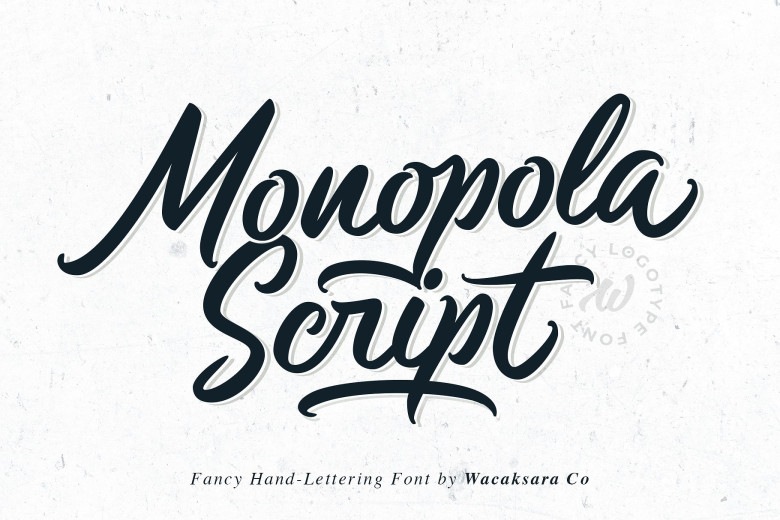
КАКИЕ БЫВАЮТ ШРИФТЫ
Если вы учились на графиков, скорее всего, вы помните основы. Если нет — я рада с вами ими поделиться! Важно отметить, что «в настоящее время общепринятая классификация шрифтов отсутствует, любая схема отражает личное мнение ее составителей». (Компания «Паратайп», paratype.ru). Поэтому нижепривёдённая классификация — это не подробная профессиональная классификация, а скорее шпаргалка для тех, кому надо вспомнить или просто полезно иметь под рукой небольшую справку.
Итак, какие бывают
шрифты? Одна из возможных классификаций разделяет шрифты по стилистическому
признаку на 4 группы: антиквы, гротески, декоративные и акцидентные, а также
рукописные и каллиграфические шрифты.
1) Антиквенные шрифты
Антиквенные шрифты (или антиквы) — это шрифты с засечками. Они могут быть контрастными или одноширинными, прямыми или курсивными, с исторической формой знака или современной. Главный отличительный элемент — засечка — может быть брусковой, треугольной, тонкой, толстой, скруглённой, острой, в общем, практически любой. Засечка всегда зависит от исторического контекста или от фантазии автора современного шрифта. Более подробно о группе антикв и их истории можно почитать в статье на Википедии (ссылка: https://ru.wikipedia.org/wiki/%C0%ED%F2%E8%EA%E2%E0). В рамках прикладной классификации («шпаргалки») можно не обращаться к истории, но для более глубокого изучения шрифтов я рекомендую ознакомиться с антиквами более подробно.
2) Гротески
Гротески, или как их
ещё называют, рубленые шрифты, это собственно шрифты без засечек.
Вначале их
использовали исключительно для акциденции, но в XX веке стали использоваться
для набора больших масс текста. Характеризуются, как правило, малой
контрастностью или полным отсутствием визуального контраста между основными и
соединительными штрихами. Иногда
к гротескам относят также так называемую ленточную антикву — умеренно контрастный
шрифт без засечек, конструкция которого повторяет один из видов антиквы. Сейчас гротески повсеместно используются в дизайне: сайтов, интерфейсов, рекламе, в журналах и т.д.
3) Декоративные и акцидентные шрифты
К этой группе относятся шрифты специально
предназначенные для акцидентного набора (то есть для выделения, например,
заголовков или важных элементов), использующиеся в декоративных целях, или
имитирующие определенный исторический стиль (например, модерн и т.д.). Форма
знака может быть изменена в целях создания определённого настроения.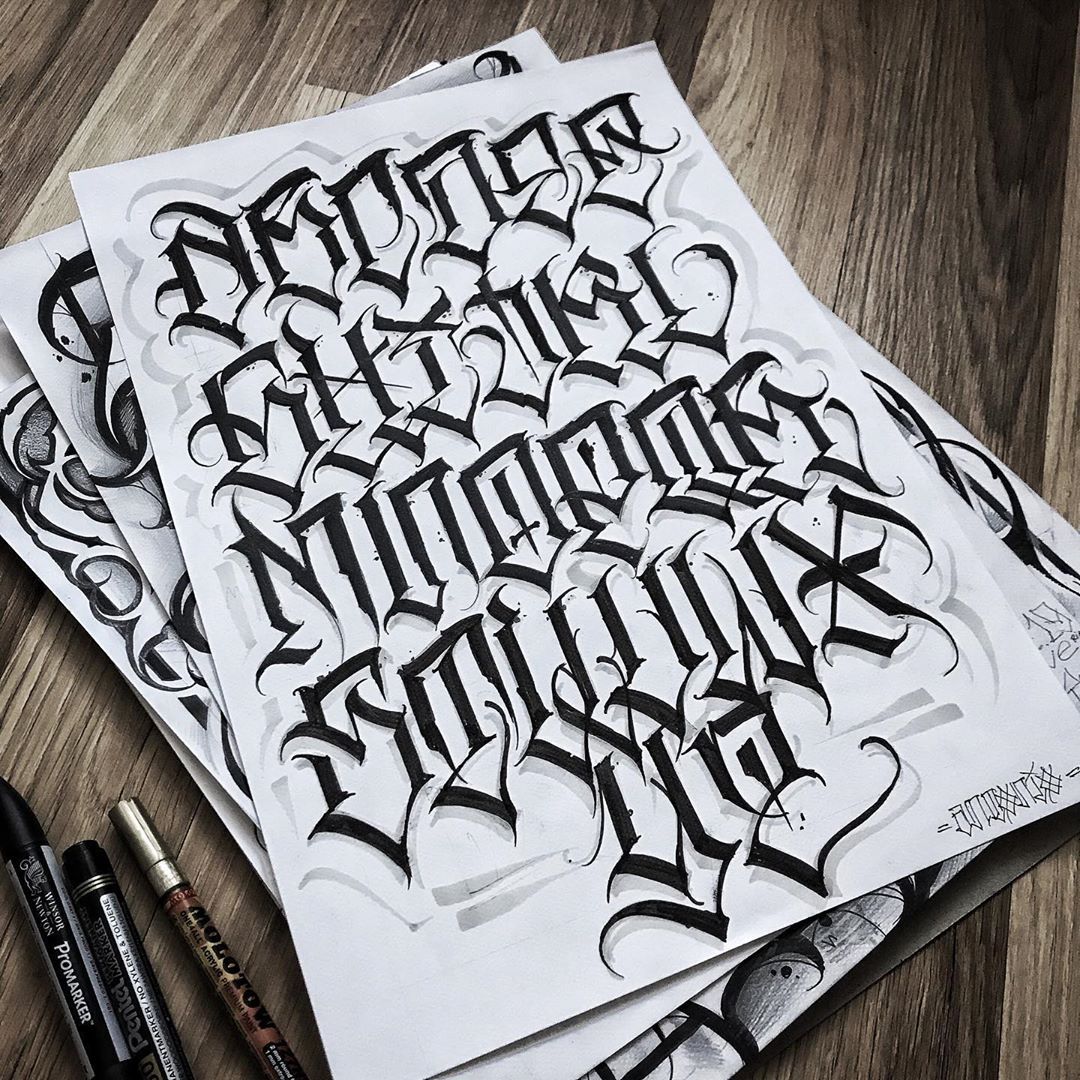
4) Рукописные и каллиграфические шрифты
Из названия этой группы следует, что к ней относятся шрифты на основе почерков (например, Пушкина) или имитирующие по рисунку каллиграфический стиль. Некоторые классификации относят к этой группе и готические шрифты. Рукописные шрифты могут быть связные (где каждая буква связывается с соседней) и несвязные (буква стоит отдельно). По функции рукописные шрифты, конечно же, используются для акциденции, и ими не рекомендуется набирать (или рисовать) большие массы текста.
На примере рассмотренной классификации я предлагаю
рисовать ваши собственные версии этих шрифтов.
Например, вы можете
комбинировать антиквенные засечки с надписью, сделанной вашим собственным
почерком. Здесь я написала Hello Spring маркером Edding толщиной 3 мм, а поверх
нарисовала засечки-кирпичики на кончиках линий. Надпись была обработана на
компьютере — об этом мы подробнее поговорим в одной из следующих статей.
Также можно сделать красивый вытянутый гротеск и дополнить его свошами. Эта работа сделана Юрием Гордоном из его шрифта Бон Валет на компьютере, но вы можете повторить тоже самое и руками.
Ещё идея: возьмите любимый наборный шрифт (то есть тот, который установлен на вашем компьютере), напечатайте его контур на хорошей бумаге, а потом раскрасьте, как вам вздумается! На самом деле это очень полезное упражнение: когда вы руками будете обводить наборный шрифт, анализируйте толщину штриха, контраст, форму, расположение засечек и т. д. И потом, это отличная медитация — вспомните, как в детстве нас всех увлекали раскраски! 🙂
А теперь пара слов о сочетаемости.
Все мы слышали, что
плох тот дизайнер, который в макете сочетает более двух-трёх шрифтов. Но в
современном леттеринге, к счастью, таких правил нет. Посмотрите, как смело и
бойко Nika Ewan сочетает казалось бы несочетаемое: антикву с гротеском,
приправляет рукописным и щепоткой декоративных элементов.
И ещё один пример: здесь автор взял два объёмных гротеска, два небольших аккуратных неконтрастных гротеска, и два рукописных шрифта с очень эмоциональными свошами. Два, два и два, при этом каждый шрифт на своей строчке. Можете взять на заметку такой способ сочетания.
Желаю вам больше смотреть хороших, вдохновляющих
примеров, не бояться экспериментировать, анализировать работы коллег, подмечать
детали, которые они используют, и не бояться переносить их в свои работы. А в
следующий раз поговорим о композиции надписи в листе и о настроении, которое